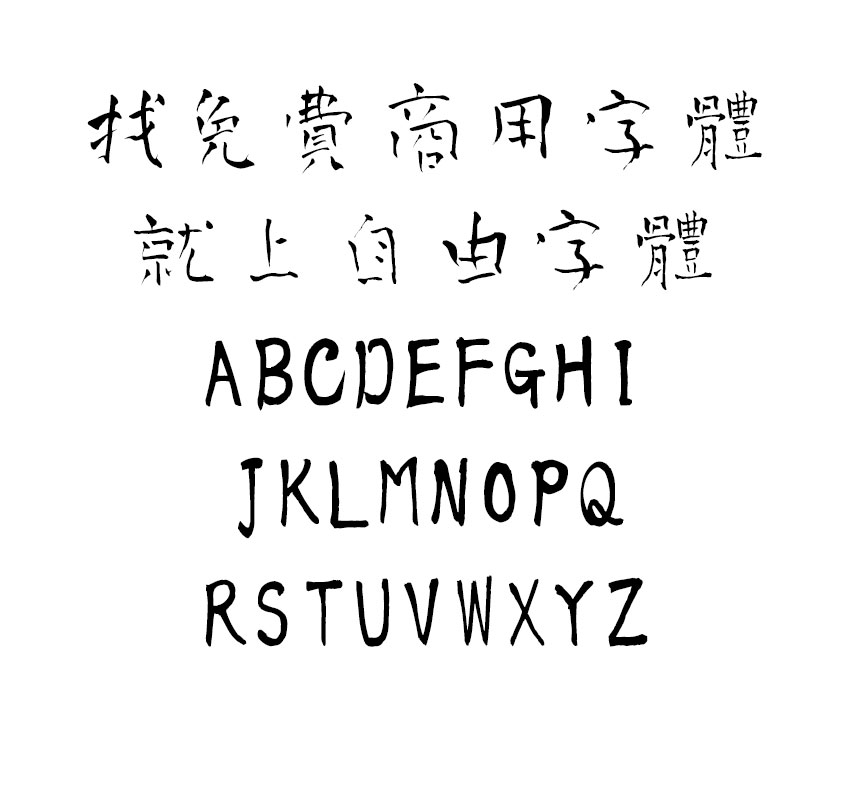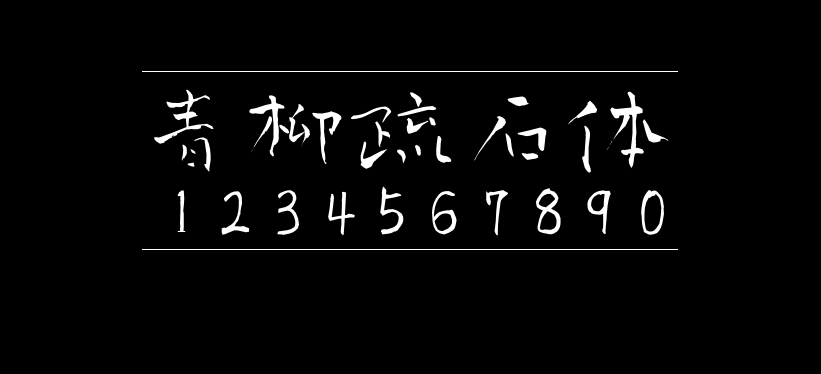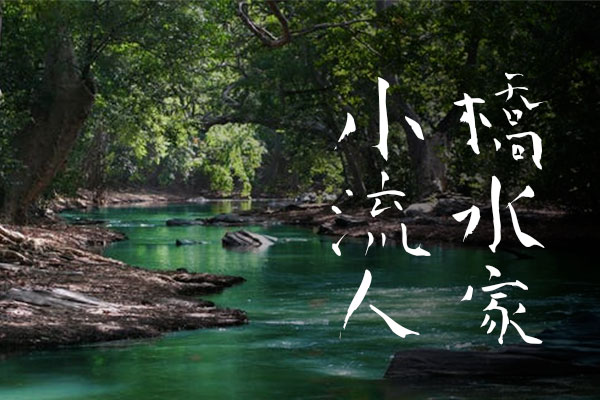
青柳疏石体
青柳疏石体(青柳疎石フォント / AoyagiSosekiFont2 )是日本书法家青柳疏石挥毫创作的书法字体,青柳衡山先生负责将其它制作成字体文件。青柳疏石体这款字体看上去并不规则,有点歪歪扭扭,很有特色,包含JIS第1水准2965字,第2水准3390字。由于字体采用的日本的JIS标准,所以支持的简体字数不多,但是繁体字还是比较齐全的。